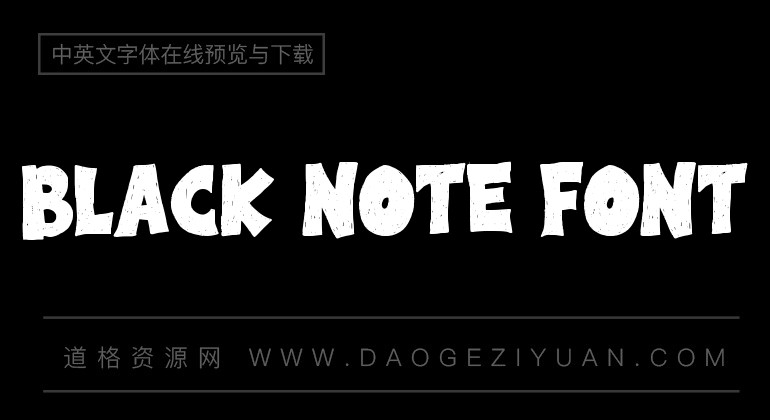
Black Note Font
Black Note Font 是一种手写风格的字体,它有一种类似于手写音符的感觉。这种字体设计简洁明了,每个字母都有明显的笔画,给人以自然、有机的感觉,非常适合用于音乐、艺术、设计等领域。 Black Note Font 字体的特点包括: 1. 手写风格:这种字体的笔画看起来非常自然,像是手写的一样,给人以亲切、温暖的感觉。 2. 易读性好:每个字母都很清晰,没有太多的花纹和装饰,因此非常容易阅读。 3. 多样性:这种字体有多种变体,包括斜体、粗体等,可以满足不同的设计需求。 总之,Black Note Font 是一种非常适合用于音乐、艺术、设计等领域的手写风格字体,它的设计简洁明了,易读性好,并且有多种变体可供选择,是一种非常实用的字体。
Black Note Font是一款非常不错的手写艺术字体,具有很好的视觉感,适合于文化类的宣传设计、商业类品牌的广告和产品包装设计以及个性化文字排版等较多场景。